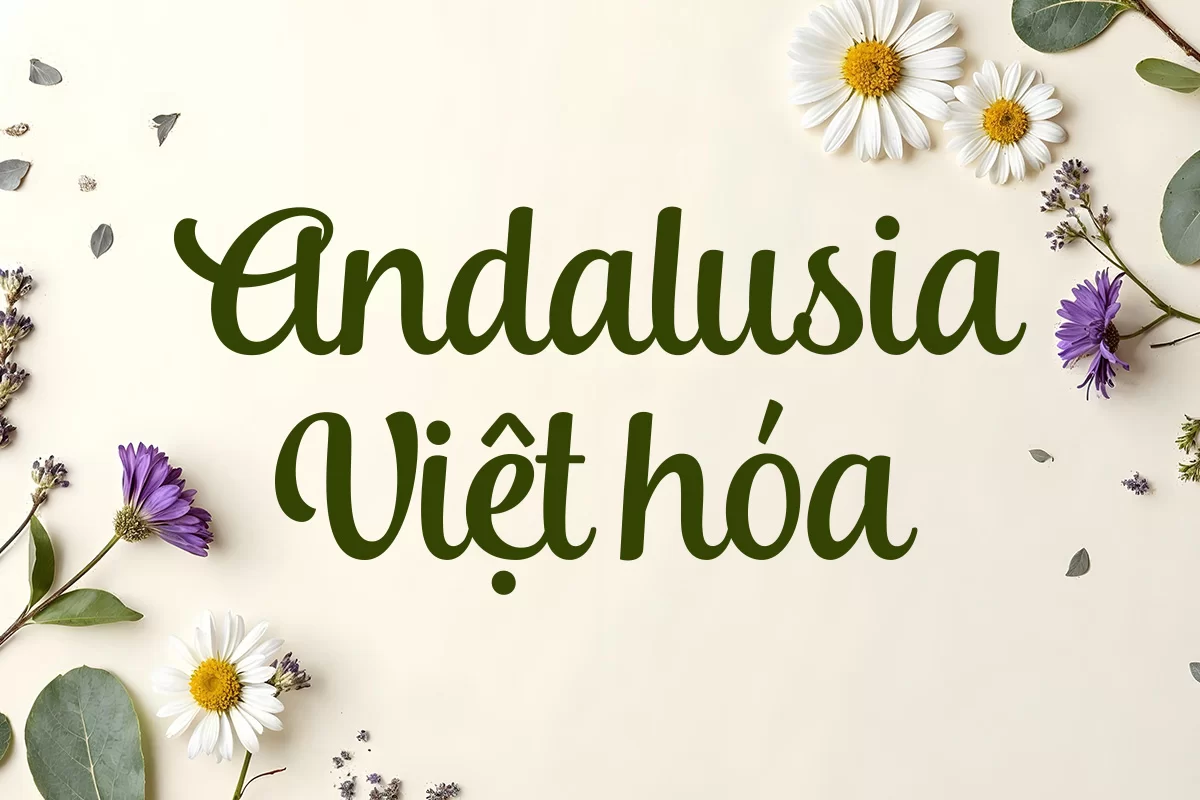
Andalusia Việt hóa là một font chữ viết tay mang phong cách script hiện đại, nổi bật với những nét cong uyển chuyển và sự cân bằng hài hòa giữa mềm mại và rõ ràng. Font tạo cảm giác gần gũi, duyên dáng nhưng vẫn giữ được sự sang trọng, rất phù hợp cho thiết kế logo, bao bì sản phẩm, thiệp cưới, bìa sách, poster hay các dự án branding cần sự tinh tế.
Bản Việt hóa hỗ trợ đầy đủ dấu tiếng Việt, đảm bảo trải nghiệm mượt mà và đồng bộ cho nhà thiết kế. Andalusia chính là lựa chọn hoàn hảo để mang đến vẻ đẹp lãng mạn và cuốn hút cho các thiết kế hiện đại.